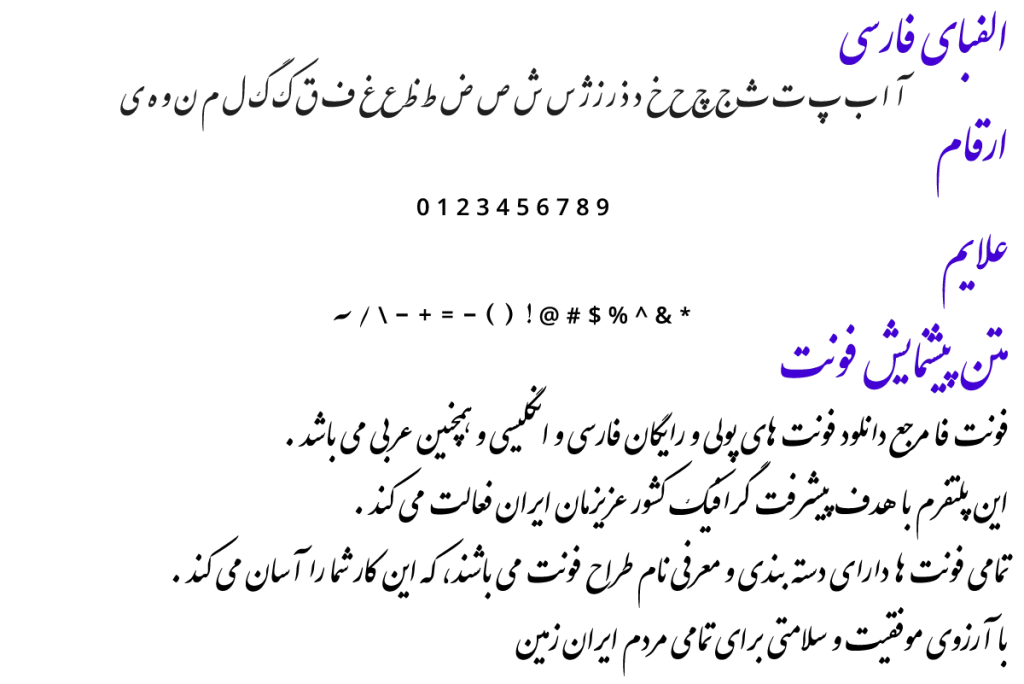
پیشنمایش فونت ایران نستعلیق
فونت فارسی ایران نستعلیق - IranNastaliq
توضیحات و معرفی فونت ایران نستعلیق
خط نستعلیق یکی از روش های خوشنویسی فارسی است، که در خطاطی از آن استفاده می شود.
اسم این خط از دو واژه نسخ و تعلیق پدیدار شده است و قدمتی تاریخی برای ایرانیان دارد.
فونت فارسی ایران نستعلیق ( IranNastaliq ) از مجموعه فونت های آزاد می باشد، همچنان نوع فونت خوشنویسی می باشد.
نسخه اولیه فونت شگفت انگیز و زیبای نستعلیق توسط حسین زاهدی در سال 1391 طراحی و ساخته شده است.
از مهم ترین ویژگی های نسخه 1 و 2 فونت به کشیدگی های در نوشته ها، تغییر فرم حروف و تغییر در جایگاه نقطه ها اشاره کرد.
آپدیت نستعلیق به نسخه 3
بعد از گذشت 10 سال از ساخت نسخه 2 این فونت، در بهمن ماه سال 1400 نسخه جدید نستعلیق یعنی ورژن 3 رونمایی شد.
در نسخه جدید تغییراتی شامل اصلاحات اصولی خطاطی و کتابت در اشکال هندسی حروف، فواصل بین آنها، اصلاح جایگذاری نقاط و اعراب اعمال شد.
همچنین ورژن 3 همین فونت با ورژن های جدید نرم افزار های مانند مایکروسافت ورد، فتوشاپ و ایلستریتور سازگار است.
فونت فوق جهت تایپ کردن مستقیم در برنامه های ویرایشگر متن و نرم افزارهای گرافیکی رایج ایجاد شده است.
با استفاده از فونت نستعلیق امکان تایپ کامل زبان فارسی و عربی بهمراه تمامی اعراب را دارد.
مقایسه فونت ایران نستعلیق نسخه 3 با نسخه قدیمی
در این مقایسه می توانید تغییرات نسخه جدید فونت را کاملا درک کنید.
کشیدگی، جایگذاری نقطه ها و فاصله حروف را به آسانی می توان فهمید.
مقایسه فونت ایران نستعلیق نسخه 3 با نسخه قدیمی
شعری زیبای وطنم با تاپ فیس نستعلیق جدید را ببینید و لذت کنید.